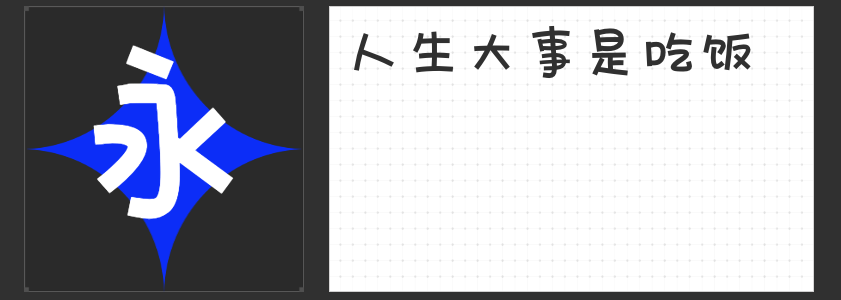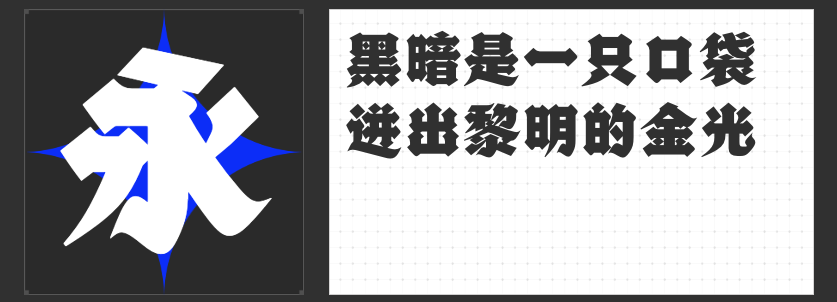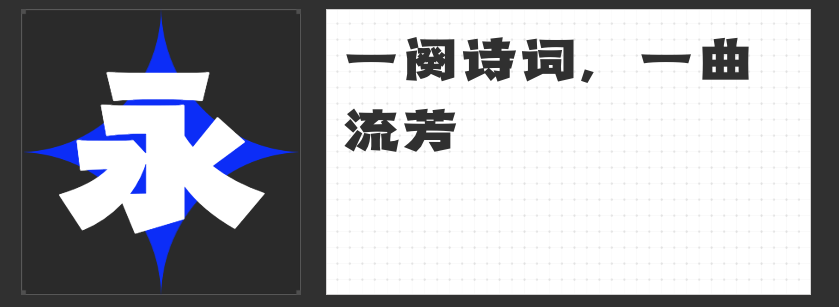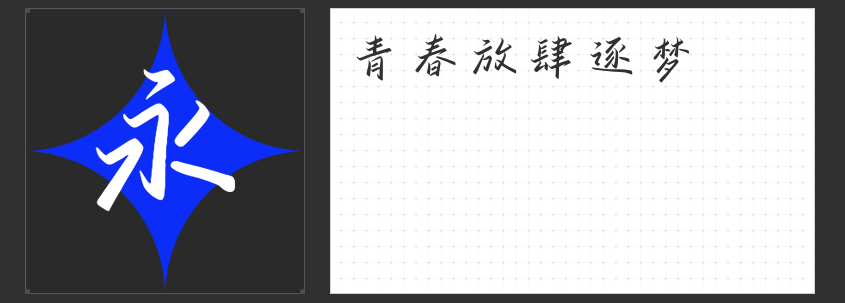
CP30开展在即,担心同人志、自印无料效果不够好?试试这四款字体!
在二次元的广阔天地里,无论是自印同人志、制作无料周边,还是设计萌系物品,字体的选择都是至关重要的一环。它能瞬间为作品增添独特的气质与氛围。今天,就让我们一起探索四款专为二次元爱好者量身定制的字体宝藏,让你的创作更加出彩!
1.古风韵味,穿越千年的笔触 —— 造字侠热辣隶简
想象一下,你的古装同人作品正需要一抹古色古香的韵味来衬托角色的风华绝代,“造字侠热辣隶简”便是那穿越时空的钥匙。这款字体以其独特的古风设计,仿佛每一笔都蕴含着历史的沉淀,特别适合用于书名、标题或是场景描绘中,让作品瞬间沉浸在古典文化的氛围中。
2.手写魅力,百变风格随心控 —— 字青春逐梦简 准粗
追求个性与自由的你,怎能错过“字青春逐梦简 准粗”?这款手写风格的字体,以其多变的线条和自然的笔触,为创作提供了无限可能。无论是温馨的日常记录,还是激情澎湃的战斗场景,它都能完美融合,展现出独一无二的个性风采。用它来书写角色独白或是旁白,定能让读者感受到字里行间的真挚与热情。
3.萌系必备,可爱满分的字体盛宴 —— 字圈也字花卷体
当二次元遇上可爱风,“字圈也字花卷体”便是那不可或缺的甜蜜调料。这款字体以其圆润的线条和俏皮的装饰元素,瞬间营造出一种温馨可爱的氛围。无论是设计萌系海报、制作周边商品,还是编写温馨小故事,它都能让你的作品充满童趣与温馨,吸引每一位喜爱可爱风格的粉丝。
4.哥特风情,暗黑与甜美的双重奏 —— 高手字斋哥特体Pro
想要挑战更加独特的风格?“高手字斋哥特体Pro”将带你领略哥特风的独特魅力。这款字体以其尖锐的线条和独特的造型,既能展现出暗黑、神秘的氛围,又能通过巧妙的搭配,展现出别样的甜美与浪漫。无论是描绘吸血鬼的优雅,还是打造奇幻世界的奇幻感,它都能让你的作品散发出与众不同的气质。
四款字体,四种风格,总有一款能触动你的心弦,为你的二次元创作之旅增添无限精彩!